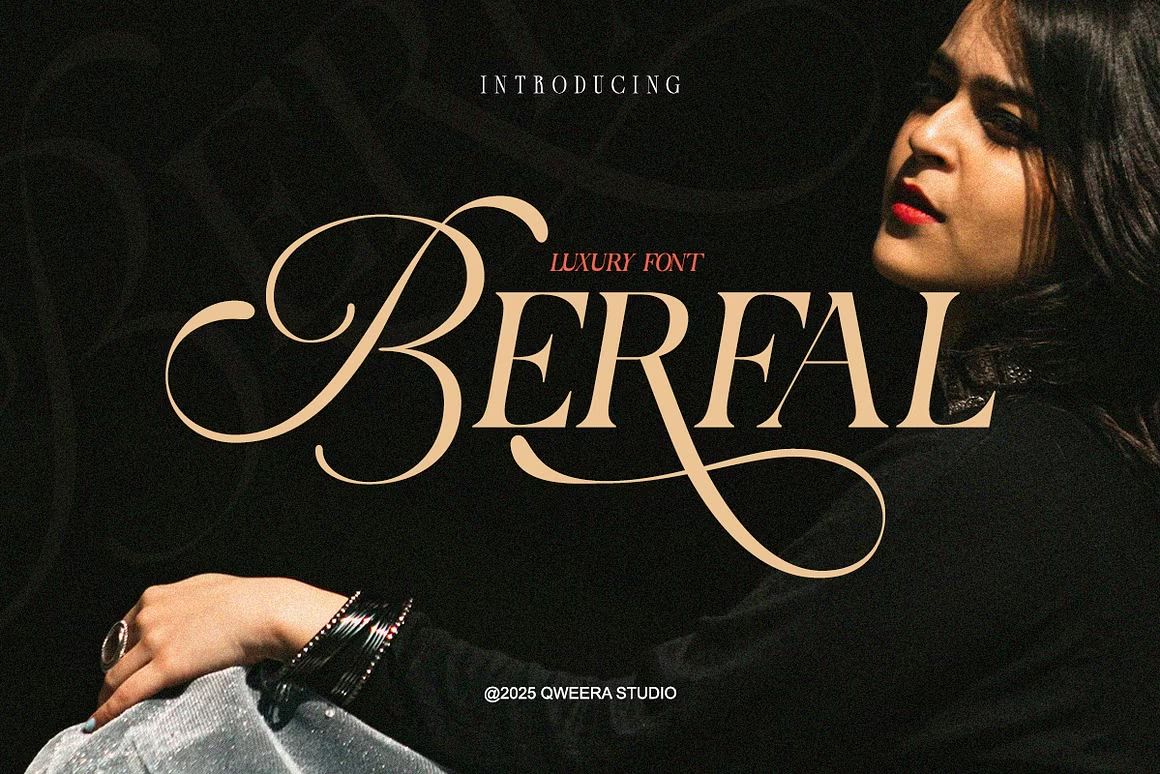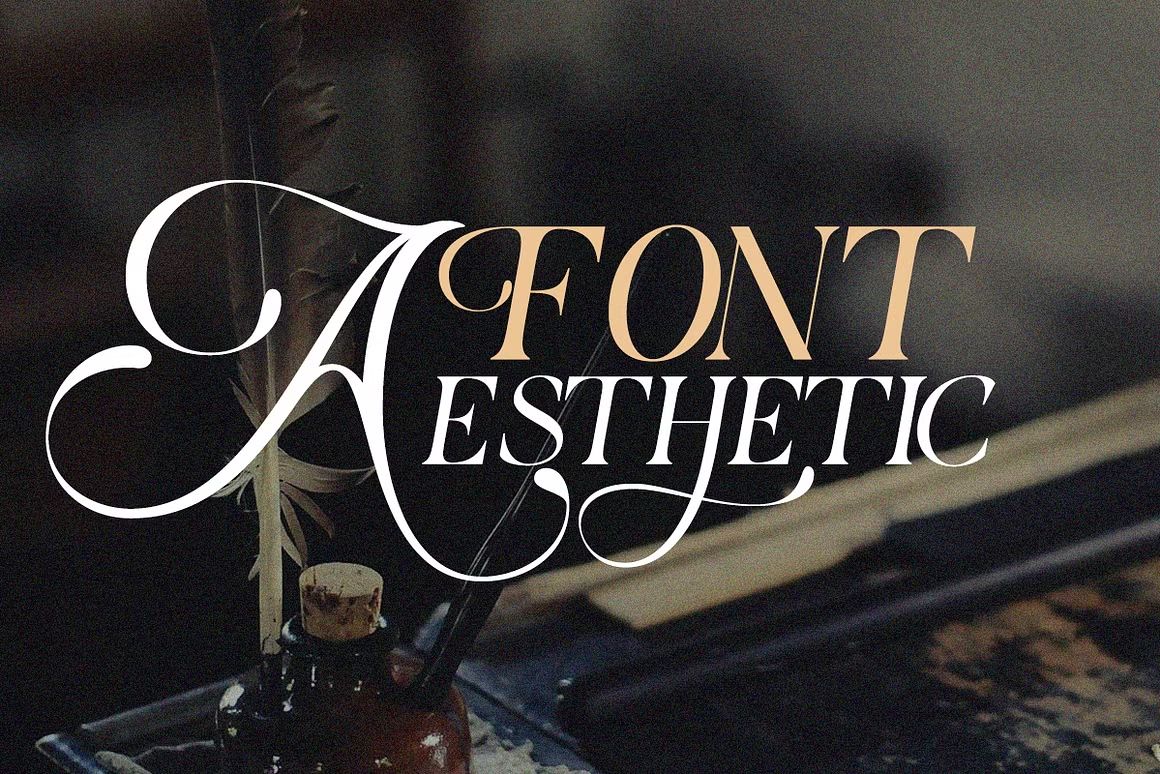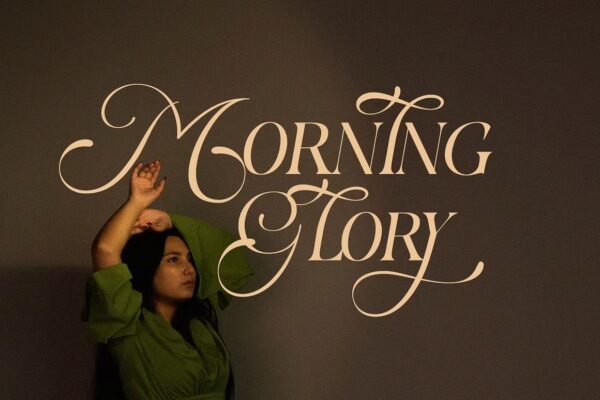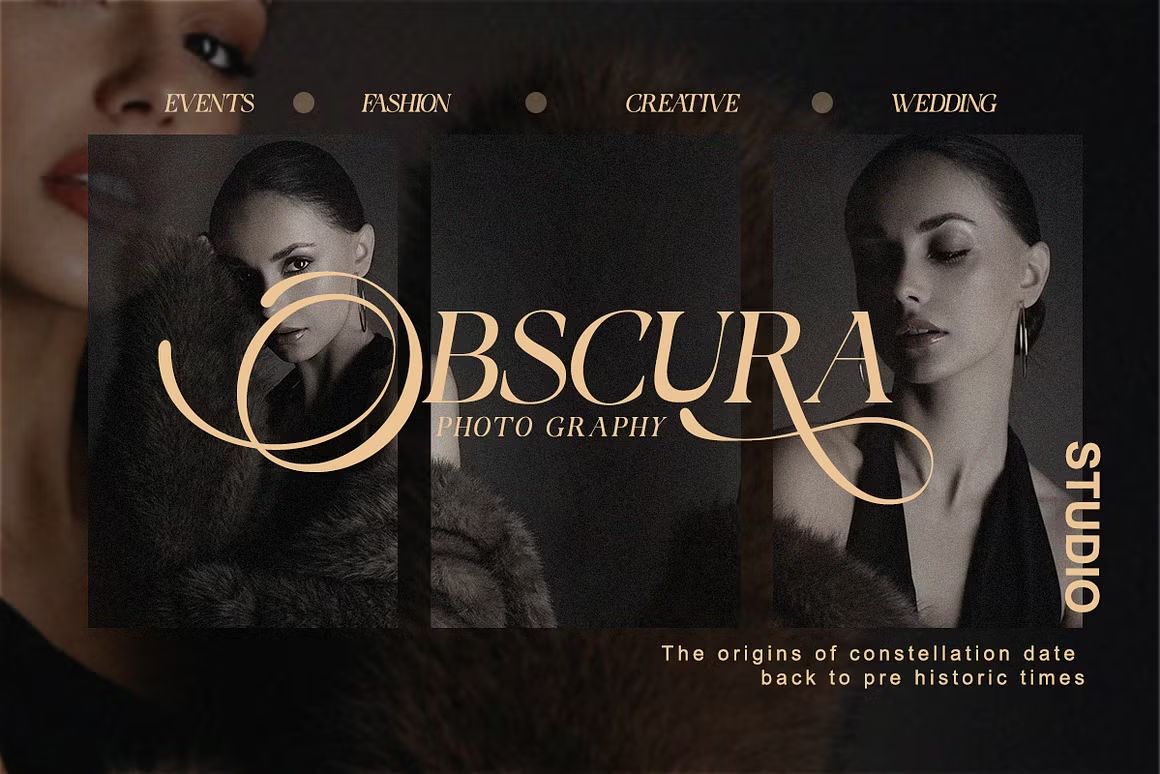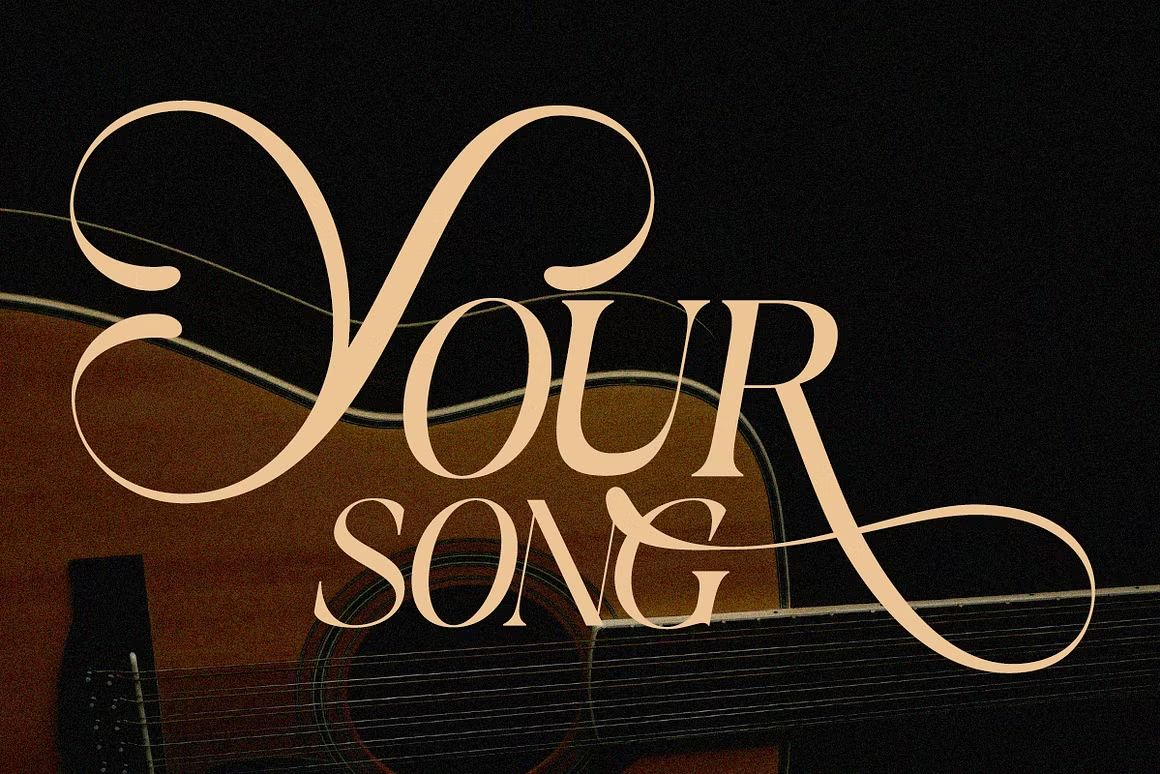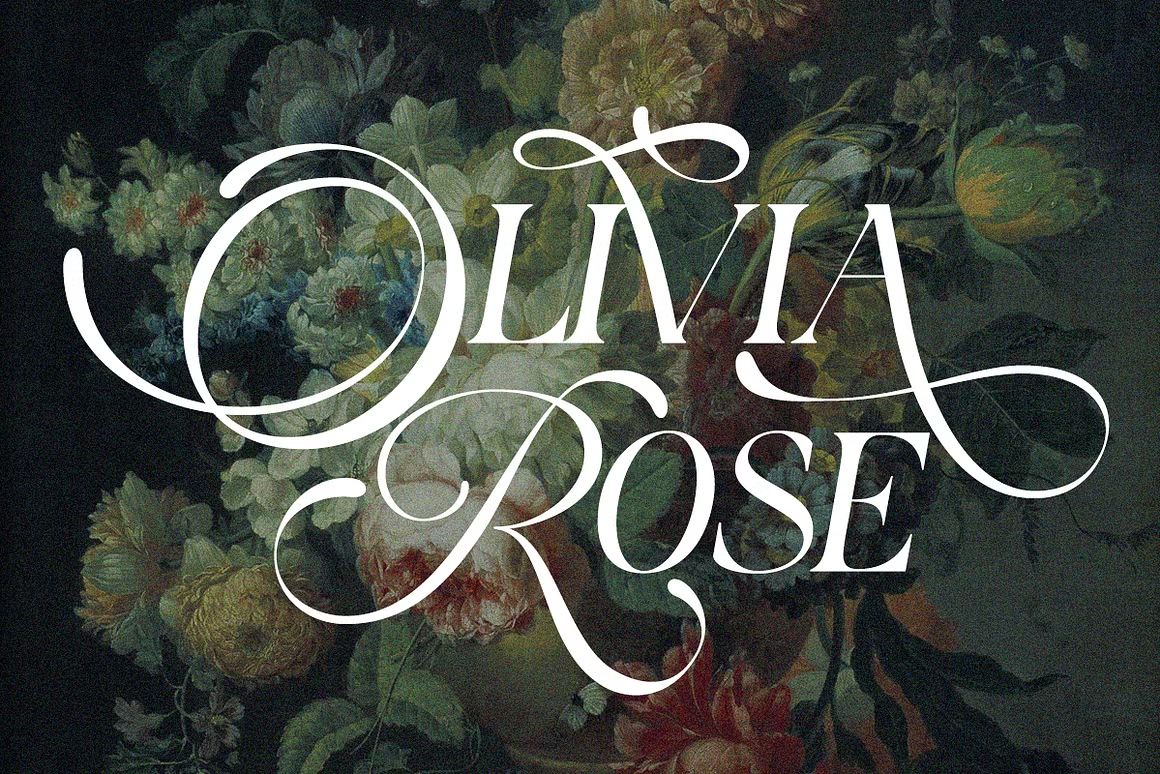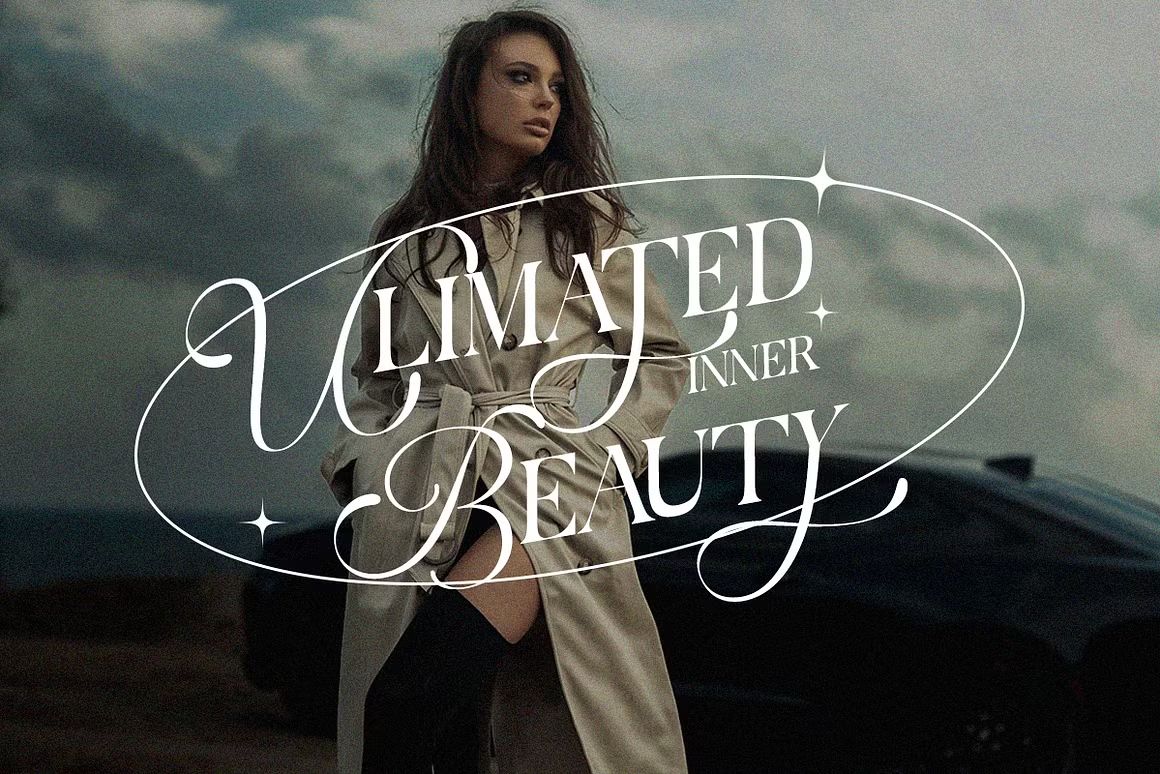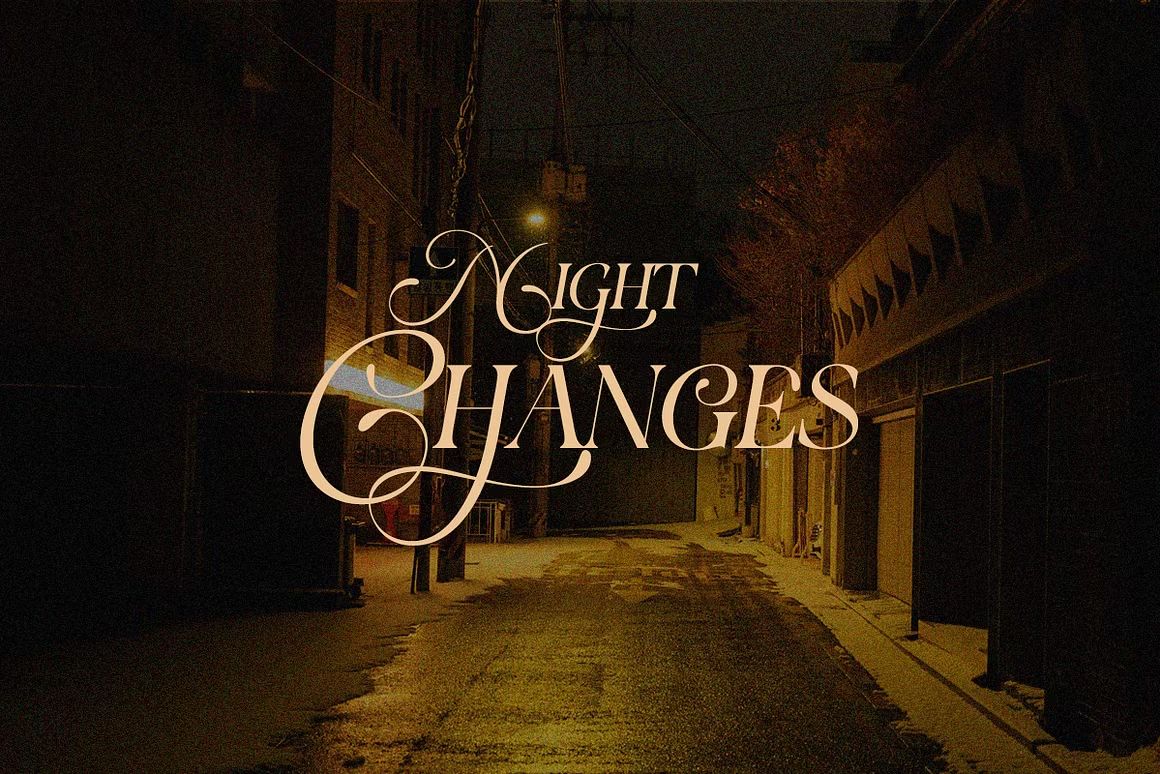
Berfal – Sans Serif Font
Berfal adalah font sans serif modern dengan garis bersih dan tegas, cocok untuk branding dan desain profesional. Format OTF/TTF/WOFF, siap digunakan.
Berfal adalah font sans serif modern dengan desain tegas dan garis bersih. Menampilkan bentuk huruf geometris yang seimbang dan mudah dibaca, font ini cocok untuk berbagai kebutuhan desain seperti branding, logo, editorial, kemasan, dan desain digital. Berfal menawarkan kesan profesional, minimalis, dan fleksibel untuk penggunaan di berbagai gaya visual.
• Desain sans serif modern dan geometris
• Cocok untuk branding, editorial, dan tampilan digital
• Termasuk huruf kapital, kecil, angka, dan simbol